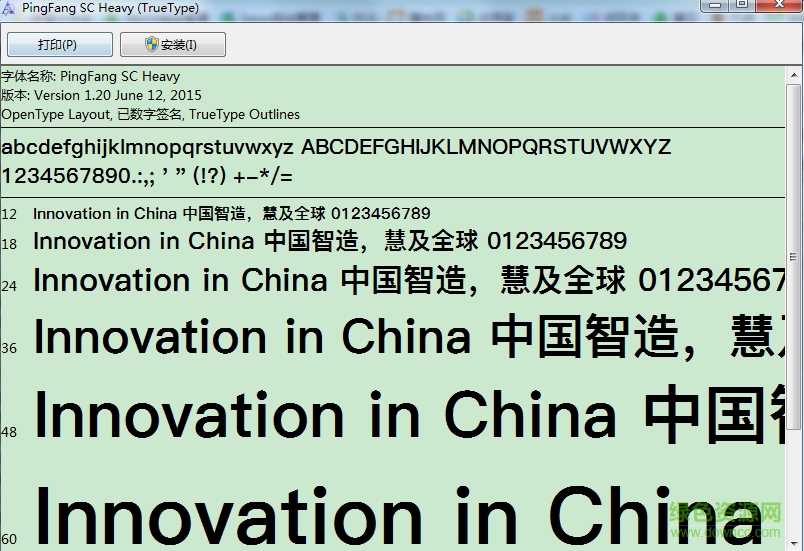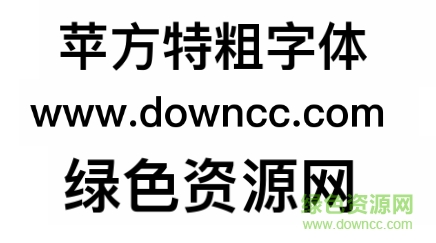
蘋方特粗常規(guī)字體
蘋方特粗字體是一款加粗后的蘋方字體,端正大氣,適合電子閱讀和各類平面設(shè)計,需要的朋友歡迎來綠色資源網(wǎng)免費下載!
蘋方特粗體介紹
蘋方特粗字體來自于蘋果系統(tǒng)中的一款藝術(shù)字體,加粗的設(shè)計讓文字顯得更加出眾有標(biāo)識性,在排版印刷、網(wǎng)頁編輯、海報設(shè)計、廣告創(chuàng)意等領(lǐng)域!